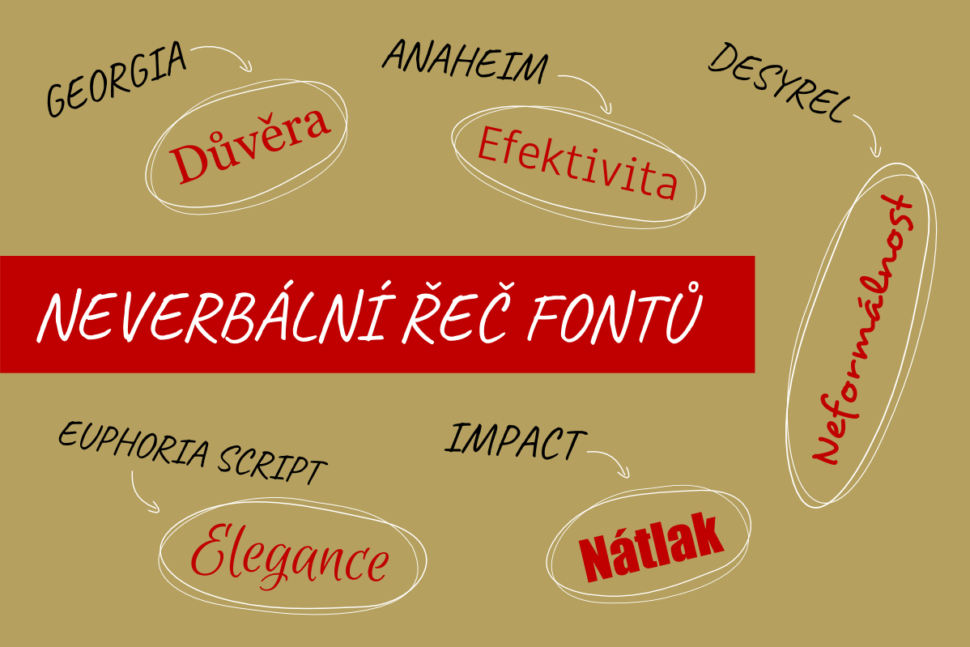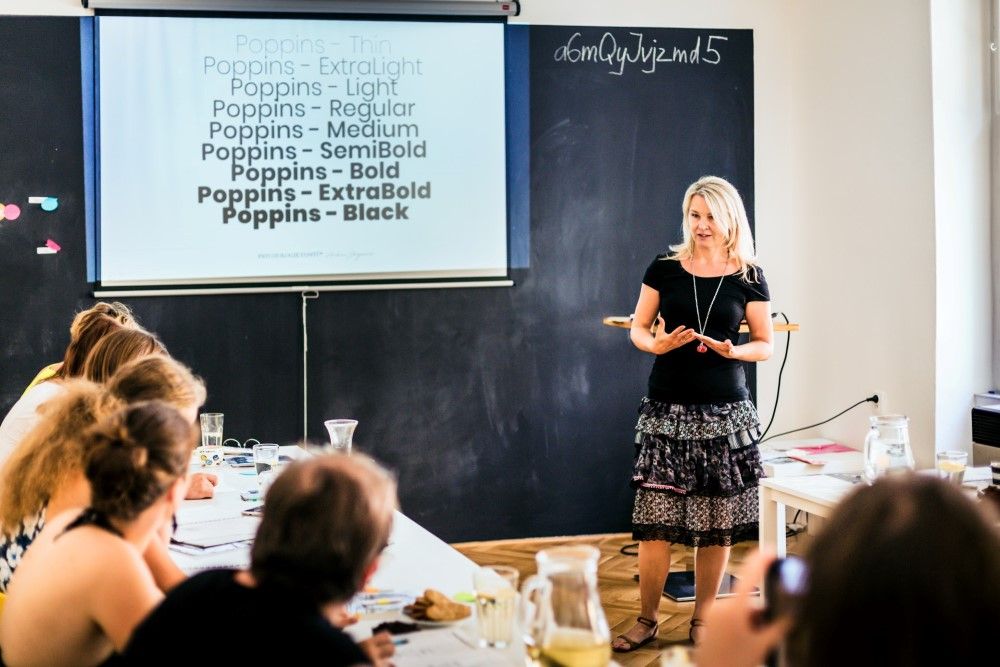
FONTY V MARKETINGU
Font je stejně silný marketingový nástroj jako barva. Umožní vám vědomě ovlivnit dopad sdělení na klienta.
Font má obrovskou moc ovlivnit vnímání čtenářů.
Dokáže budit emoce i oslovit konkrétní cílovou skupinu.
Dokáže také přitáhnout pozornost tam, kde potřebujete (třeba na to správné tlačítko) anebo vyhrát prezidentské volby.
Zkrátka a dobře, v online i offline světě není možné oddělit formu a obsah textu, a z marketingového hlediska dokáže právě font sám o sobě zásadně ovlivnit to, jak vnímáme obsah sdělení. Je v něm důvěra a spolehlivost, nebo lehkost a nadsázka?
Psychologie fontů je marketingový nástroj, který využijete při:
- přípravě či posuzování tištěných či on-line marketingových materiálů
- zacílení kampaní na konkrétní persony
- odlišení i sladění produktových řad
A jako vítaný bonus vám neuvěřitelně ulehčí komunikaci s grafikem, budete umět jasně specifikovat své požadavky a vyhodnotit dodané návrhy.
MARKETÉŘI O PSYCHOLOGII FONTŮ:
„Font, použitý na webu nebo na vizitce, vyjadřuje osobitost, ovlivňuje vnímání a dokresluje celkový dojem. Má moc přitáhnout ty správné klienty a odradit ty ostatní. Dovoluje vyjádřit atributy, jako je důvěra, jednoduchost, péče, něžnost nebo síla. Proto dává smysl věnovat volbě fontu stejnou pozornost jako výběru barev, ilustračních fotografií nebo sloganu. A proto považuji psychologii fontů za velmi užitečný marketingový nástroj. “